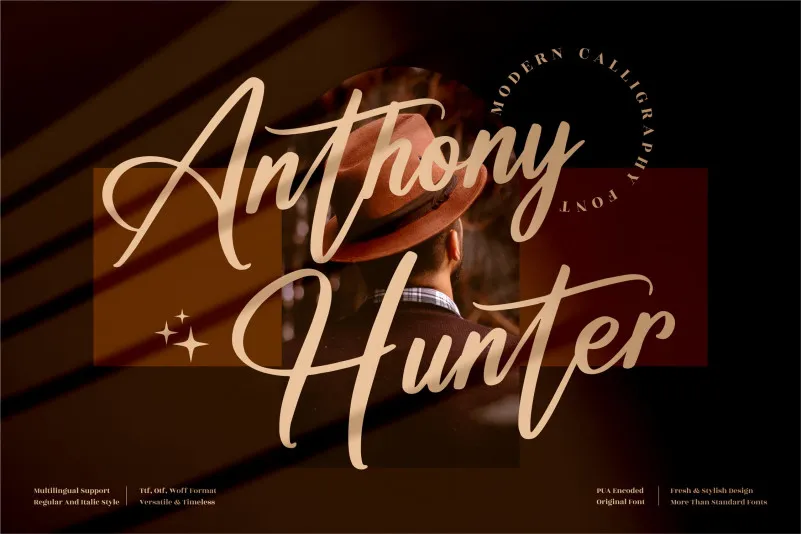
A fonte ‘Anthony Hunter Font’ é perfeitamente adequada para projetos de alto padrão que exigem um toque sofisticado e elegante, incluindo logos, produtos personalizados, embalagens de produto, materiais de decoração, nome cards, convites, cartões de agradecimento, etiquetas, fotografias e até mesmo marcas em eventos especiais. Seja para projetos criativos ou tradicionais, esta fonte garante uma identidade visual impecável e um toque de classe única que se encaixa perfeitamente com sua marca ou projeto. A sua elegância natural faz deste um recurso indispensável para qualquer designer profissional ou amador que está em busca de qualidade superior e sofisticação nos seus projetos. Com a ‘Anthony Hunter Font’, você pode garantir que seu trabalho seja lembrado não apenas pelo design, mas também pela perfeita mistura de elegância que essa font oferece.